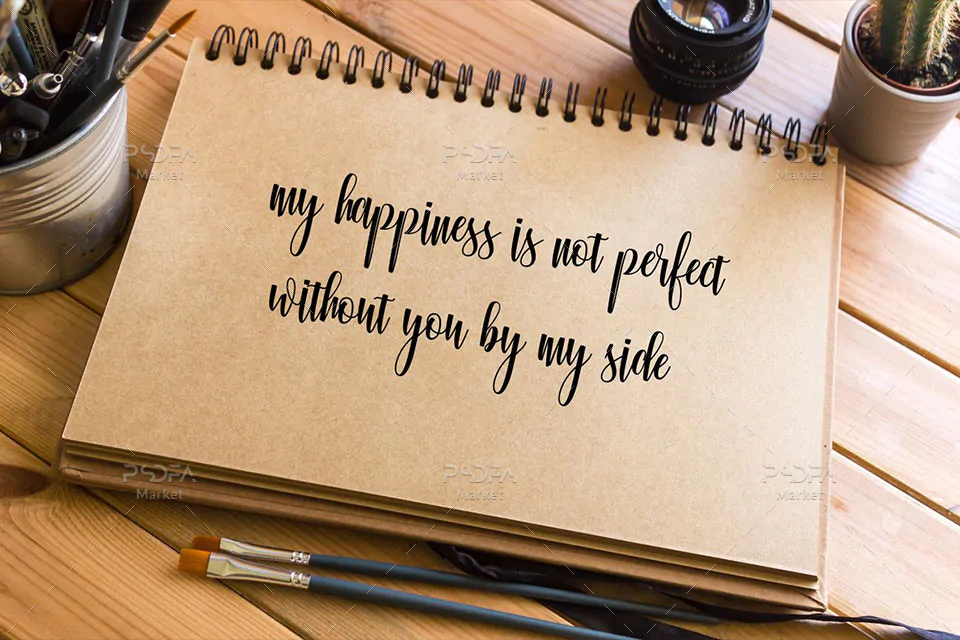
فونت انگلیسی دستنویس Glorious Calligraphy یک قلم انگلیسی فوق العاده زیبا است که مناسب جهت استفاده در طرحهای گرافیکی مختلف به خصوص طراحی انواع کارت تبریک میباشد. این فونت زیبا در قالب 2 فایل OTF, TTF در فایل محصول قرار دارد که با نصب یکی از این 2 فرمت در پوشه فونتهای سیستم میتوانید از این فونت انگلیسی در تمام نرم افزارهای گرافیکی و تایپ متون همچون فتوشاپ، افتر افکت، پریمیر، ورد، پاورپوینت و … استفاده کنید.
فونت دستنویس Glorious Calligraphy در وزن معمولی (Regular) طراحی شده است که میتوانید از آن در طراحی انواع کارت تبریک، کارت پستال، کارت ویزیت، کاور آلبوم موزیک، طراحی انواع بنر، پوستر، تراکت، تقویم، طرحهای ولنتاین و دیگر طرحهای گرافیکی استفاده کنید.
- نام فونت: Glorious Calligraphy
- وزن: Regular